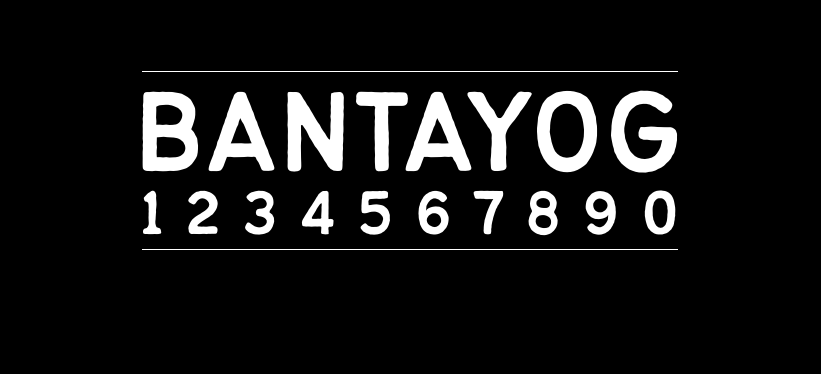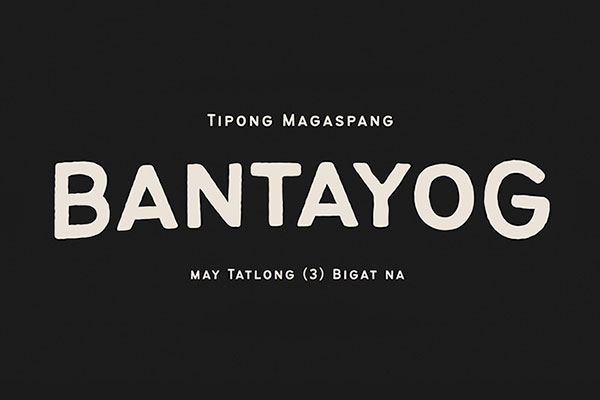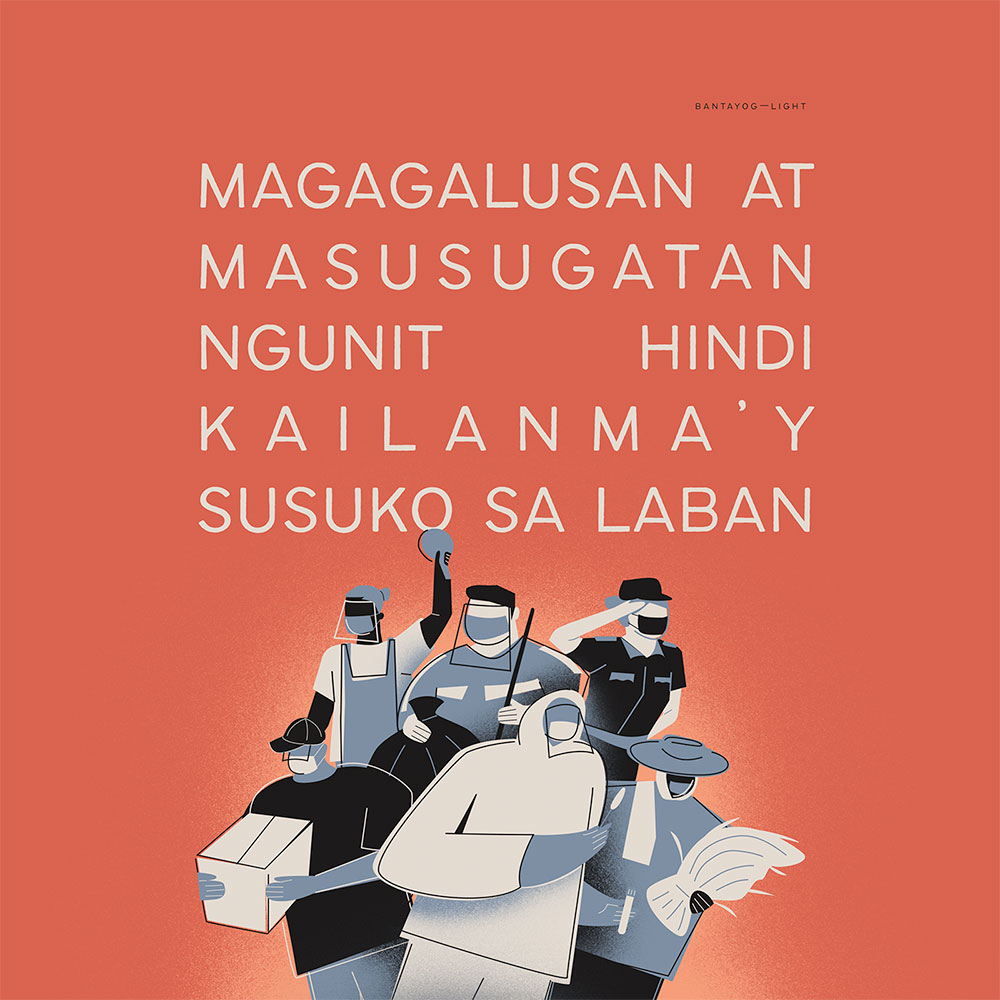
Bantayog
Bantayog的作者是菲律宾的John David Maza,自由字体之前已经发布过他创作的另一款字体Maragsâ,有兴趣的可以了解下。
Bantayog字形非常特别,粗看像圆体,但是仔细看你就会发现,它的线条是粗糙不平的,作者在圆体的基础上增加了铸铁磨损的修饰,使其具有年代感,可以用于描述过去的重大事件以及历史标记记述的著名民族人物的生活。
Bantayog是菲律宾语中的“纪念碑”,旨在提醒今世后代的英勇行为,并在人们展现和奉献之前牺牲人民,并唤醒每个人的爱国精神,以纪念英雄们的记忆。作者的创作灵感也就是来源于纪念碑上的粗糙文字。
字体创作于2020年8月,作者希望通过字体的形式,向新冠病毒期间奋战的医护人员表达敬意!